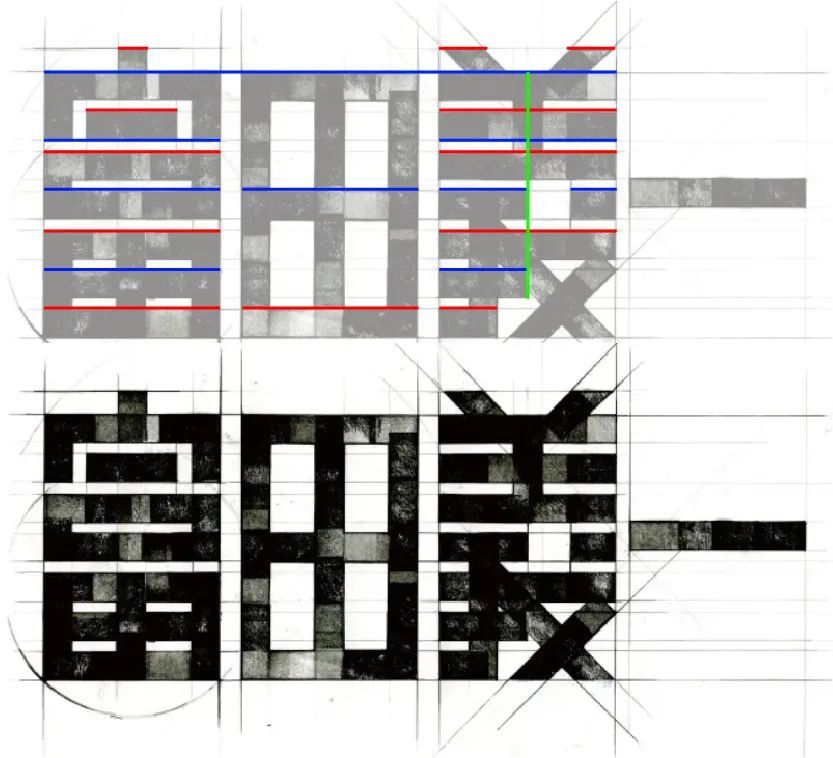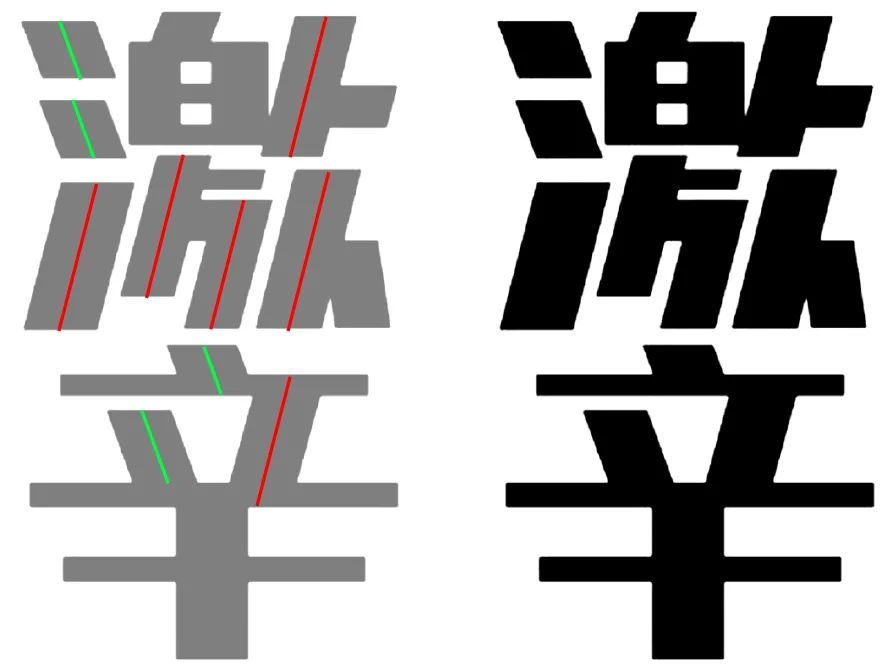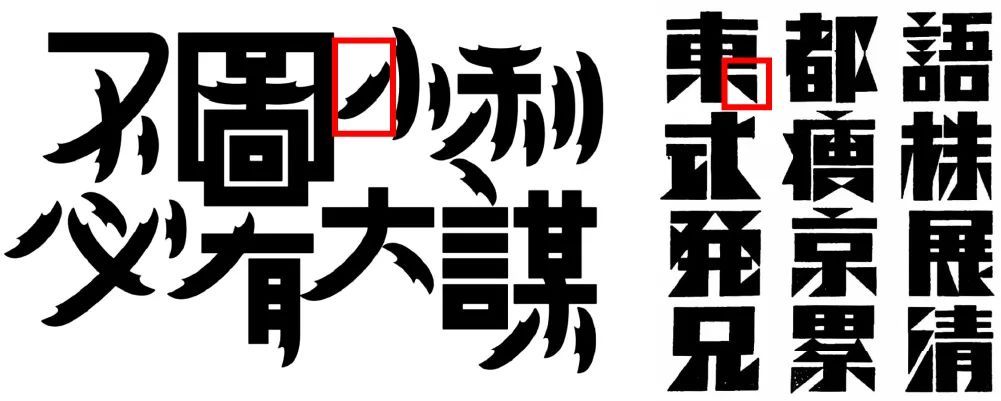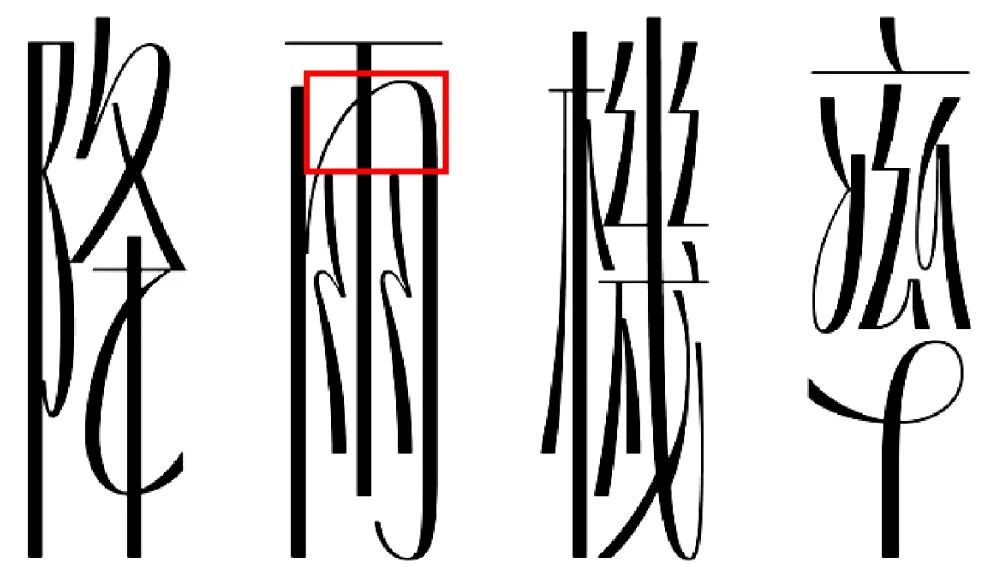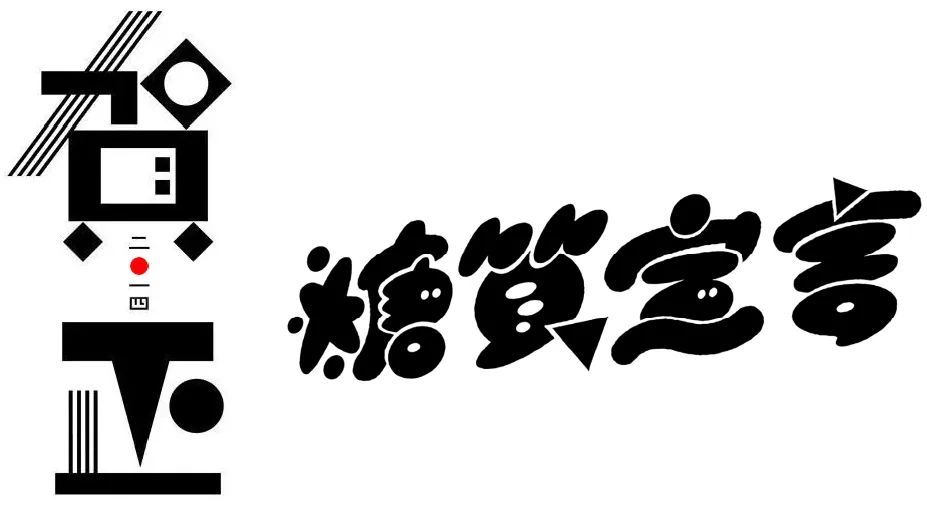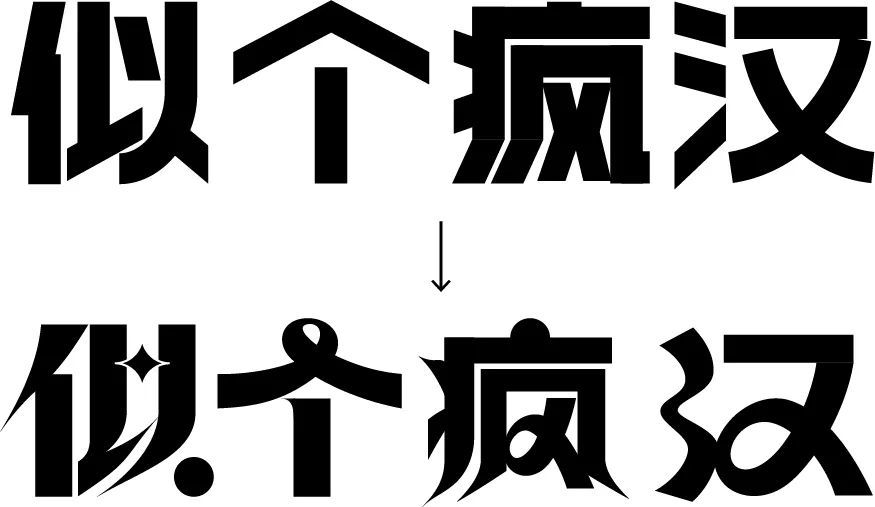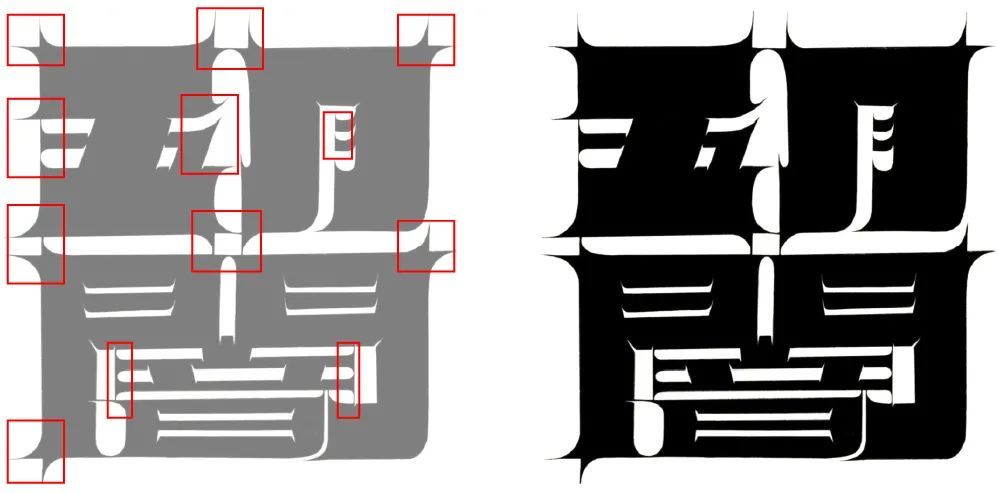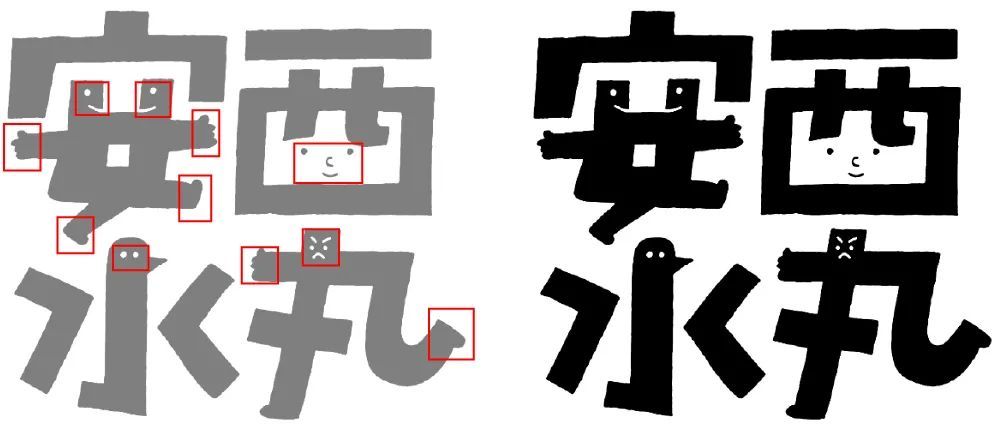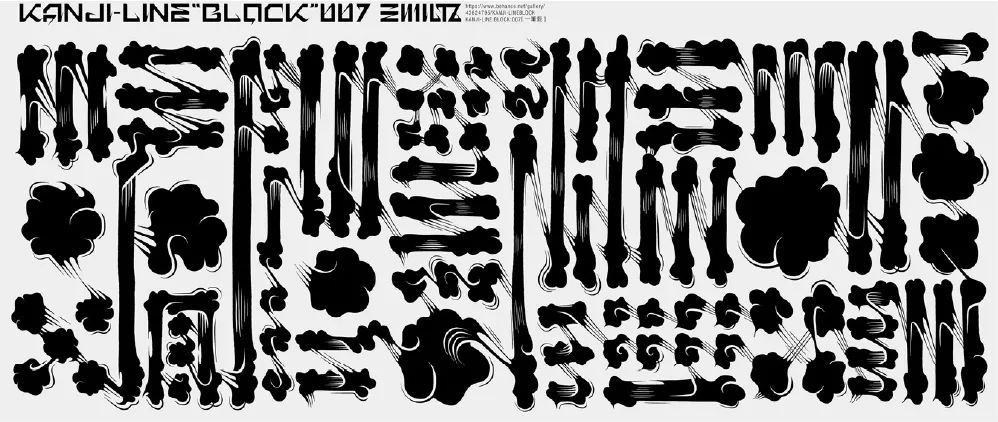
提升字体设计综合水平的五个共性
今天我们来聊一下字体设计中的「共性」,经常能看到这样的处理,却又很容易被大家忽略。做共性其实就是去做统一,这种做法的好处就在于会看到一种和谐又自然的设计感,且视觉表现力不会那么浮夸,所以自然也就容易被忽略掉。
这篇干货教程来自猴子老师。他将其大致分了五大类,其中还有一些小的细节,我们逐一来看一下,开整!
1、对齐
2、角度统一
3、笔画设定统一
5、灰度统一
首先第一点肯定是对齐,最基础也最简单,但就算是一个简单的对齐也是有一些不同细节区分和需要注意的,我们结合下面的例图慢慢来看。
① 常规对齐
单个字外围能对齐的部分尽可能去对齐,该居中的就居中对齐,形成一个矩形状。
每个字尽可能等宽等高(有些字不具备等高的条件,如下图的「一」字),且字与字之间能对齐的横笔也要尽量去对齐,这样会形成一个非常秩序和谐的整体。但要注意单个字的笔画分布的合理性、匀称性。
下图中给大家用红蓝线画了一下字与字之间横笔对齐的部分,避免线条过多太乱。
可能有同学会有疑问,为什么田字顶部的横笔没有跟富和義字的顶部对齐呢,这主要是考虑视觉对齐的因素,人的眼睛是有视错觉的。
如果把田字顶部横笔直接对齐到最上面,那会看起来会觉得田字比其他字要高,因为田字顶部的横笔远比富字顶部的点和義字顶部的倒八字头要重的多。这里就不再多说了,有机会我们单独开篇来讲一讲字体中的视错觉问题。
单独看上面的例子还感觉不出什么,下面我放一个常规的黑体来对比,大家可以观察一下区别和对齐的部分。
② 局部对齐
顾名思义,只是把整组字的局部去做一个对齐,使整体有一定的设计感及趣味性,其主要的难点就在于需找出一组字当中适合做对齐的位置,这个「适合」尤为重要,既能增强秩序性,又不会像常规对齐一样呆板,多了些灵动性。
不知大家观察完上面四组例子之后有没有发现什么细节,除了第一组例字之外,剩余的三组都有一个共性,每组字都会有一个较多字共同参与的对齐,在此之外还有有一些局部的小对齐,这便是细节的体现了,可以进一步增强整体的趣味性和秩序性。
③ 强制对齐
这一点相对来说要更难一点,因为涉及到了笔画变形的问题,所以可能性就变得更多了,那么具体的做法其实也就是向内压缩空间,当笔画足够粗的时候就可以强行改变笔画原有的位置,使其对齐。
为了便于大家观察,下图中我把正常黑体的字摆在一旁。
需要注意的就是并不是所有字都可以这样处理的,所以大家切勿钻牛角尖。
还有一点就是字的内部空间的匀称性,以及笔画变形的合理性,因为这样强制去处理对齐,势必会在识别上造成一定的影响,所以识别度也是需要着重考虑的一点,如果实在太低,那便放弃。
又到了案例实操的环节了,但这里其实没有太多思路性可谈,照上面总结的去做就可以了,不过后续抽空可以给大家录制视频版的制作过程。
角度统一相对对齐来说,难度上会有所增加,因为会涉及到更多的笔画变形处理以及结构上的调整,但也是有一定的规律性在的,大致也是分了三个小类别,下面我们结合例字逐一来看。
① 常规角度统一
首先我们要知道角度统一的是什么,横竖笔画固然是不变的了,那统一的无非就是撇捺点这些非横竖的笔画,清楚了这一点就容易的多了,但仍需注意结构的稳定性。
通过上面两组例字我们会发现,角度设定的越大,统一起来就会越难,甚至要做到很夸张的笔画延伸和结构变动才能使整体稳定下来,所以初学时不宜设定太大角度。
另外一个小细节不知道大家发现了没有,两组字当中,横竖笔画的切角也全部都是统一角度的。
② 特殊角度统一
常见的特殊角度就是 45 度和 60 度,45 度是非常好用也是很出效果的一个角度,但缺点也很明显,处理起来会相对困难。
60 度反而更简单一些,因为可以利用网格来进行制作,只要在网格内按照角度去划分笔画就好了。
ps:不要问为什么没有 30 度和 90 度这种问题......
上面三个例子都是 45 度的处理。
60 度网格处理形式。(案例跟网格有少许差距,不是准确的 60 度,请忽略不计......)
可以看到上面 45 度的例子中,有结构改动较大的,有矩形状的,其实还是要由你所做的字来决定。并不是所有字的撇捺改成 45 度后都能做成个矩形状的,且还要有笔画变形的能力,至于 60 度的例子更多是技法类的了,有时间我们单独开一篇来讲一讲字体中的一些技法。
③ 多重设定角度统一
当一个角度无法满足整组字或难度过高时,可以采取这种方法,设定多个角度去统一,以此来降低难度,保留秩序性和设计感的同时也能给整体增添一些变化。
相同颜色为同一角度
观察后可发现,虽说角度可以设定多个,但尽量避免太多,否则便失去了角度统一的意义,与常规字体无异了。两到三个便足够,再多就不合适了。
首先这一方法需要根据你所做的字,来选择更为合适的角度统一方式去做,这里我演示的字是之前在站酷作品中出现过的「破」字,那我们首先把要做的字打出来并观察需要统一角度的笔画。
观察上面标红的笔画,其实只有右半部分的皮字左侧的竖撇统一起来是有点难度的,其他的笔画本身的角度就比较相似,所以处理起来并不会太难整。下面就需要尝试去画草图了。
可以看到直接按照基础的黑体结构来做是不太现实的,那么问题主要就是我们上边提到过的那一竖撇,且整体的稳定性稍差,所以需要对结构有些轻微的变动,如果大家把控不好的话可以多去找些字库、古籍字等作为参考去处理。
上图中找了三种看起来比较容易做角度统一的字库作为参考,得出三种不同的结果,这里我选择的是最后一个,整体更加稳定,且舒适度最高,下面根据草图继续往下做。
可以看到在我们用矩形工具去绘制完成后又有了新的问题,空间极其不匀称,主要体现在右侧的皮字部分,上面很挤,下面很空,所以我们还需对空间进行再次优化,那其实因为笔画角度的问题,已经很难再去调整了,这时候我们就需要对笔画进行加粗和减细的处理,来达到负空间尽量均衡的状态。
大家可以对比观察一下调整的部分,因为牵一发而动全身,所以这一步需要反复去调试,直至负空间看起来均衡舒适为止。下面我们可以再去多做一些细节,让整体更具视觉张力。
最后搭配英文进行排版,这里我就是按照中文的角度去简单处理了一下拼音部分,同时根据搭配英文的感觉又尝试了一些细节的变化,大家自行观察即可。
最后选择合适的一组做一个简单的视觉呈现和小效果。
小结:
① 草图的尝试很重要,初稿的效果不理想不一定就是完全不可行的,要多去尝试不同结构和细节带来的变化。
② 草图往往是比较细的,在加粗后一定会有空间上的问题出现,所以要多去调试。
③ 多字不一定适合我上面演示的例子,要选择适合所做字组的统一形式。
这里说的就是通过笔画本身的造型来体现设计感,所以做法也并不难,只需要设定一些笔画的造型并且统一起来就可以了。
① 常规设定
笔画造型其实是非常多变的,日常所看到的往往都是跟字库的字体笔画非常接近的形态,但其实你可以把笔画定义成各种各样的造型。
图片
像上图中设定成不规则形态的,几何形态的,从粗到细过渡非常明显的形态,但要注意的是这些笔画往往都是撇捺点这一类的,横竖笔画往往比较少做变动,因为会很难把控,出现混乱的局面,总结起来其实就是一句话,设定笔画的规则,统一笔画的设定。
② 特殊形式
上面讲到的主要还是一些常规的变形手段,那自然还有一些特殊的样式和形式,归根结底还是基于词义和想要表达的主题来设定这些笔画造型,但难度肯定是要更高的。
图片
云雾、笔刷、几何、糖的造型,都是很直观可以看出来的,对于我们表达词义有非常好的帮助,但其中的难点也是不少,笔画造型越特殊,规范性、稳定性、识别度就越难做。下面我们再来演示一组看一下。
图片
像上面的很多例子的笔画都是各种不同的造型,那我们在做的时候其实也可以去找一些形式来作为参考,这里我借鉴的是一张日文的笔画处理。
首先我们拿到参考后一定要去分析其中我们可以提取借鉴的地方,那么像上图最为特殊的部分就是连笔以及粗细过度非常明显的处理方式了。记住了这两点我们就可以开始搭建基础字形了。这里做的字忘了是在哪里看到的一个词了,感觉整的挺好,当时就做了一下。
图片
基础字形搭建完成,平平无奇,毫无亮点,甚至有点磕碜(东北话,丑的意思)。反正就整得不咋地,下面我们开始结合上面的参考来替换一些笔画。
图片
嗖的一下发生了很大变化对不对,所以一找到一个好参考并分析提取出其中的优点是非常重要的,上面的笔画变形几乎大部分都能从参考中找到类似甚至一样的造型,没有的笔画其实也就是一些连笔而已,大家只需要根据手写习惯去连就好了。最后可以再根据整体的调性去增加一点小修饰。
简单给个小倾斜,与这种尖尖的笔画和修饰很搭配,最后选择合适的字体进行排版就完成了。
图片
还挺好整的是吧,别跑,接着往下看,下面我们再来一个更好整的。
图片
这一点应该是大家喜闻乐见的了,给笔画加装饰,加细节,加各种天马行空的造型,帅就完了......这点相对来说要容易一些,只要你能正常的搭建出一组字,就能做到修饰统一,但其中的分类依然不少,下面继续来看一下。
1、① 笔画外部修饰统一丨(统一笔画修饰的造型)
首先第一点就是大家最为经 常见到的这种标题字形,在笔画的边缘处去添加一些修饰的造型,来起到表达词义或强化视觉表现力的作用。
虽然说在笔画的边缘处添加修饰这一说法很好理解,但其中还是存在一些细节。我们一起来看一下上图中,添加修饰的笔画和位置基本上都是左上角,横笔、竖笔以及横竖转折处的左上角,这便是规律。
至于到底要在哪里去添加这些修饰,完全取决于你自己,但要注意一些空间非常小的地方就不适合去添加这种修饰了,会影响到整体的笔画识别和空间上的不舒服。
图片
这个案例相对于第一个案例,添加的修饰显得更为丰富,但也是同样是有规律的。横笔的四个角,竖笔的四个角,全部都有添加同样造型的修饰,修饰多了,所以视觉上看起来就更为丰富,但并不是说修饰越多越好,设定的规律越多,便越难统一,甚至杂乱无章,适合才是最好的。
② 笔画外部修饰统一丨(统一笔画修饰的特征)
上面讲到的是统一笔画的造型,也就是修饰的造型全部都是一样的,那么这一点虽然也是类似的处理方式,但在造型上稍微有所区别,并不是每一个修饰都完全长的一样。
图片
可以看到上面两组案例中,添加的修饰并不是都完全一样,但看起来也是非常和谐的,适当分析便可得出规律性所在,首先造型类似,与笔画的连接极其自然顺滑,而不是生硬的凹造型去结合,大小适当变化增添节奏感和视觉变化的感受。
上面演示的和分享的案例都是偏现代的字形,最后再给大家分享一些我做的偏古风一些的字。
图片
大家应该能很清晰地看到,上面的每组字当中都存在着很多相似的处理,这也是共性和统一。其中部分是复刻字形,所以共性这一规律在字体当中是从古就存在的。
所以今后在做字的时候多想一些「共性」这一点,相信会对大家做字也有非常大的帮助,做字会更加规范,秩序,合理,舒适,不要总想着花里胡哨的,那些你看似很花的字其实当中也蕴含着很多共性。
最后再来总结下今天所讲的重点内容:
1.对齐、角度统一、笔画设定统一、修饰统一、灰度统一。
2.多看,多去找参考,善于发现和提取所用到的内容,多去尝试。
3.同一组字中不止一种共性存在。
这次的分享就到这了